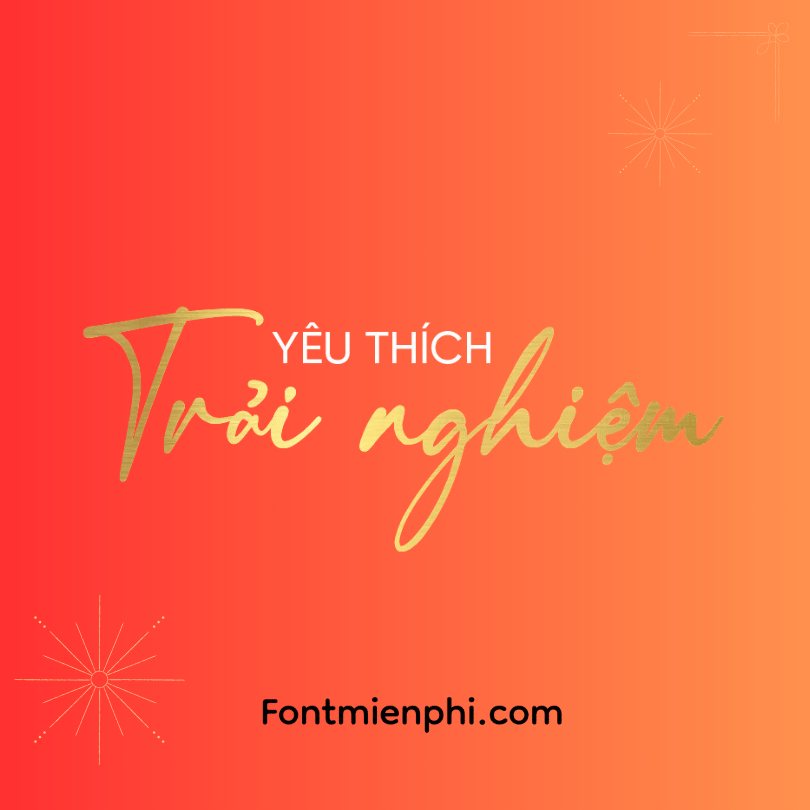
Font Việt hóa 1FTV VIP Thirty Script
Font Việt Hóa 1FTV VIP Thirty Script – Nét Chữ Thanh Lịch Đầy Cảm Xúc
Đặc điểm nổi bật:
• Phong cách handwriting sang trọng với các nét thanh đậm tự nhiên
• Hỗ trợ đầy đủ bảng mã Tiếng Việt (Unicode)
• Bao gồm 3 phiên bản: Regular, Bold và Shadow
Ứng dụng lý tưởng:
✔ Thiết kế logo thương hiệu thời trang cao cấp
✔ Bao bì mỹ phẩm – nước hoa sang trọng
✔ Thiệp cưới – Wedding invitation
✔ Menu nhà hàng – Café cao cấp
✔ Banner quảng cáo thẩm mỹ viện